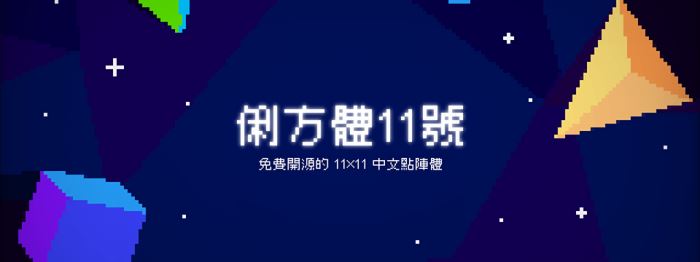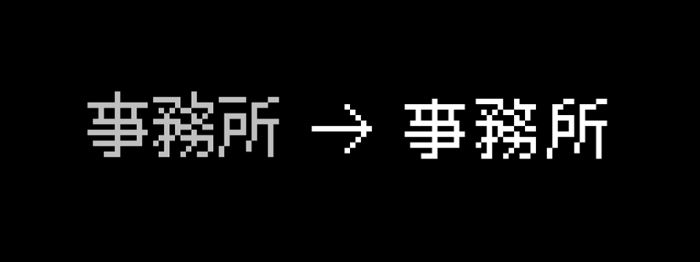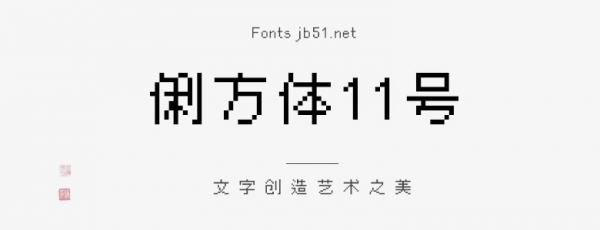
俐方體11號是一款基于M? gothic 12r衍生的開源繁體中文點陣字型,可用于像素風(fēng)格的游戲以及美術(shù)當(dāng)中,具有很好的視覺感,適合應(yīng)用于藝術(shù)設(shè)計、平面宣傳設(shè)計、網(wǎng)頁設(shè)計,書法字帖等領(lǐng)域,需要的朋友可以前來本站下載
字形調(diào)整
本字型以日文字型 M? gothic 12r 為基礎(chǔ)替繁體中文進行修改與擴充,其中包括適用繁體中文的標(biāo)點符號以及較符合臺灣地區(qū)習(xí)慣的字形等。(字體在電腦中顯示的名稱為俐方體11號)
收錄字數(shù)
常用國字標(biāo)準(zhǔn)字體 4808 字。
Big5 第一字面 5401 字。
IICore 臺灣常用字 T1A、T2A 及部分 T2B。
臺客閩粵字。
注音符號。
GB 2312 Level-1。
通用規(guī)范漢字表 一級。
元素週期表之所有元素字符。
字數(shù)統(tǒng)計
下面這個圖統(tǒng)計了這款字體里面包含多少個簡體字數(shù)和繁體字數(shù)等信息,方便大家直觀地了解這款字體的簡繁字體數(shù)量。中國大陸的小伙伴只需特別關(guān)注GB2312和3500字常用漢字表的數(shù)量就可以了。